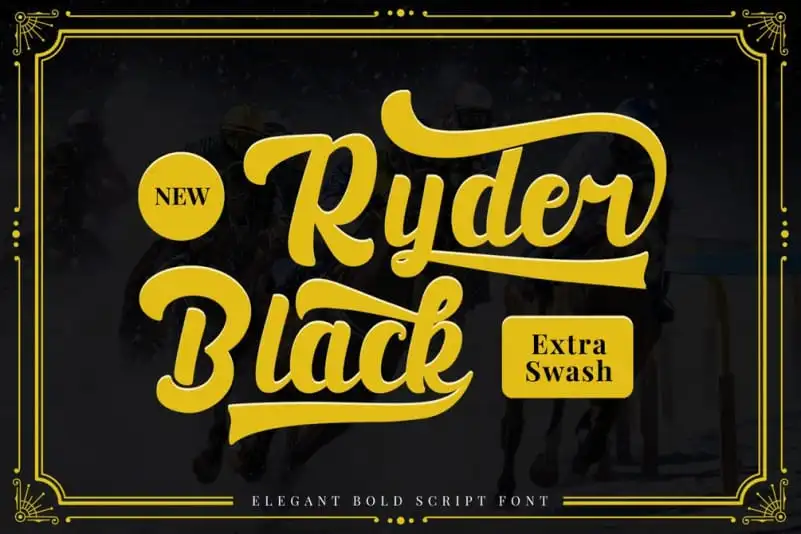
Black Ryder – Bold Script Font – Download Grátis
A Black Ryder é uma fonte em estilo script bold que traz linhas elegantes e fluidas ideais para criações variadas no design gráfico. Esta fonte foi projetada pelo designer Naharstd e pertence à categoria de Brush Fonts, o que a torna perfeita para ambientes tanto elaborados quanto simples. Seja você um estilista criando roupas com uma identidade visual moderna, um profissional de marketing buscando expressar sua marca de forma única, ou até mesmo alguém interessado em personalizar material de consumo como camisetas e sacolas, a Black Ryder será uma escolha ótima. Suas linhas fluidas oferecem o equilíbrio perfeito entre clareza e sofisticação. Com ela, você pode criar desde cartazes para eventos especiais até capas de livros e revistas em um único projeto, criando uma identidade visual coesa que se destaca. Obrigado a designers e especialistas em design por adicionar esta fonte excepcionalmente funcional à sua galeria de recursos. Seja você um designer gráfico profissional ou alguém iniciante buscando adicionar novas opções ao seu arsenal, Black Ryder será uma excelente escolha para levar seus projetos do papel para o mundo.